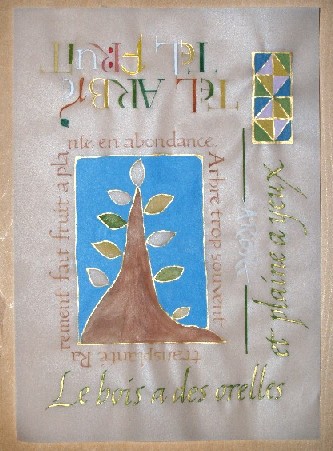
フランスから
年末にフランスからメールが届きました。
昨年の秋にパリへ行かれたmocoさんからです。mocoさんはパリにぴったりのと〜っても可愛らしい方ですが、実は芯がとてもしっかりしている素敵なカリグラファーです。
これは彼女の作品。水の中のイメージで描かれたそうです。たしかにそんな感じ!プクプク水の中から泡が浮いていくみたいです。
そしてこれも面白いのです。
トレーシングペーパーに書いたそうです。この少ししわになったところがいい感じですね。この半透明なテクスチャーとつやは、ヴェラムに似ています。絵も描いてあるし金箔も貼ってあります。厚めのトレーシングペーパーはいろいろな事が出来るんですね。可能性を秘めているのかも!
それにしてもパリでカリグラフィーの作品を制作する。